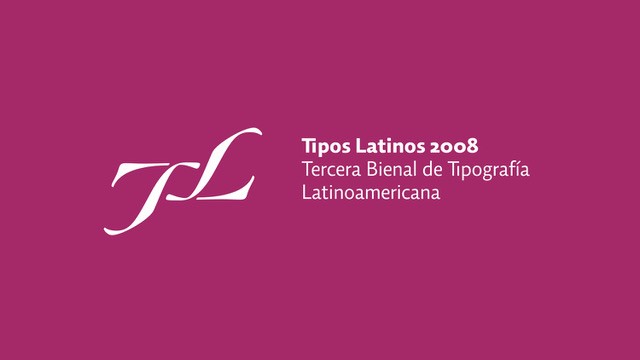
2008 Jura
Jura Tipos Latinos 2008
En un ambiente ética y humanamente cálido se desarrollaron las sesiones de la jura. Dos jornadas largas de 8 horas sirvieron para evaluar los trabajos presentados. La selección se realizó en tres rondas sucesivas. En la primera se observaron el total de láminas; algunas se reubicaron de las categorías en que originalmente fueron inscritas por el autor, y se eligieron 206 trabajos que obtuvieron el voto de al menos uno de los miembros del jurado. En la segunda ronda se seleccionaron 94 proyectos que recibieron como mínimo cuatro votos del jurado.
En la tercera y última ronda se definieron los 79 trabajos de la colección. Las sesiones y las rondas, se caracterizaron por intensas etapas de diálogo, donde cada jurado pudo manifestar sus puntos de vista en torno a los trabajos.
En términos generales, los trabajos presentados reflejan madurez y manifiestan una vez más, que la producción tipográfica latinoamericana sigue en constante evolución.
Si observamos a detalle los resultados de la presente bienal, podemos observar que en la región continúa el interés por las tipografías para título y una inusitada tendencia al impecable desarrollo del diseño de fuentes y familias tipográficas para textos. Latinoamérica es un campo fértil para que la tipografía, siga dando buenos frutos.
Francisco Calles
Tipos Latinos México
Luciano Vergara Chile
Diseñador gráfico graduado en el Duoc UC, durante el año 2003 cursa el Diplomado en Tipografía de la Universidad Católica de Chile. Desde el 2002 se desempeña como diseñador de información en oficinas de ingeniería, trabaja como freelancer en diseño editorial para reparticiones públicas y como docente en diversas universidades e institutos en Chile, realiza charlas y talleres en diferentes instituciones de educación superior chilenas. Colabora en publicaciones chilenas de diseño y tipografía. El 2004 diseña las tipografías Sinaptix y Byp01 para oficinas de ingeniería de Concepción. En el 2007 participa como parte del equipo chileno de proyecto Demo 2007. En el 2004 fueron seleccionadas para la Bienal Letras Latinas sus tipografías Patúa y O-Higgins, el 2006 fue seleccionada su fuente Revolución.
A partir del 2006 distribuye en la fundición T26 sus tipografías Otto, Pepona, Roketu, Trauco y Los Lana. Desde el 2007 distribuye sus tipografías Chilean bugs y Fidel en la fundición chilena Latinotype.
Ignacio Martínez-Villalba Colombia
Diseñador gráfico egresado de la Universidad Jorge Tadeo Lozano. En 1989 continúa estudios de ilustración y tipografía en el Colorado Institute of Art (Denver, USA); en 1996 y 1997 participa en seminarios sobre tipografía y diseño del cartel; de 1999 a 2000 recibe el Master de Diseño Editorial en la Universidad de Barcelona. Desde 2004 realiza una investigación en esta universidad para el doctorado en tipografía. Esta abarca la historia tipográfica de los siglos XIX hasta mediados del XX, sus procesos, las fundiciones y artistas del libro de la misma época.
Desde 1991 diseña carátulas e ilustra libros para las editoriales Norma, Fondo de Cultura Económica, Siglo del Hombre Editores y Alfaguara en Colombia: y para la editorial de la Fundición Jordi Goli Gurina y la Agencia de Publicidad Llorente en Barcelona.
Juan Carlos Darias Venezuela
Diseñador gráfico desde 1986. Se desempeña como director diseñador de la revista Clips, director de arte de la revista Popder Joven, miembro de la Galería de la AVAP y director académico desde 1989 en diferentes institutos de diseño, como ISA e IDA. Funda y dirige el Instituto de Diseño Darias (1996). Es responsable del diseño de catálogos. folletos y revistas para hoteles Sheraton, Museo de Arte La Rinconada y la Galería de la AVAP, entre otros. Director de arte y articulista de la revista especializada en diseño Logotipos, es asesor y miembro honorario del Congreso Internacional de Diseño Gráfico (COIDIGRA) en Mérida (Venezuela). Es instructor en el área de extensión de la Universidad Simón Bolívar y amigo de ICOGRADA Se desempeña como conferencista en eventos nacionales e internacionales como Congreso Internacional del Diseño Gráfico de Mérida (2003, 2004, 2005), la Semana del Diseño en Sao Paulo (2004), la 8 Bienal internacional del Cartel en México (2004), Historia del Diseño en Venezuela en la Universidad Anhembi Morumbi en Sao Paulo Es curador participante y organizador de diversas exposiciones. Es investigador de la historia del diseño gráfico en Venezuela, coordinador de la muestra de la Bienal Letras Latinas 2004 en Caracas y la Galería IDDAR en 2005 y curador y diseñador de la muestra El Quijote Gráfico. 400 años del viaje de aquella triste figura (2004). Integró el jurado de la Bienal Letras Latinas en representación de Venezuela y llevó la muestra a Venezuela en 2006.